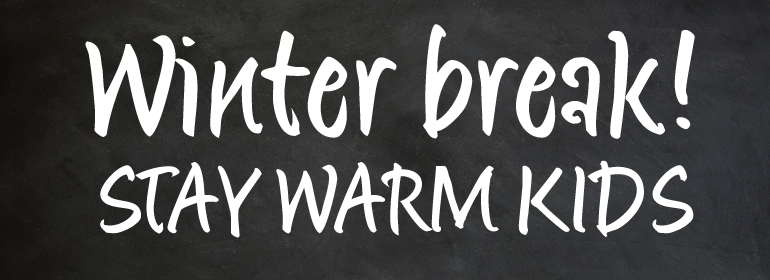
Matthia™
字体品牌: Linotype(Monotype) 设计师:Kurz,Dieter 字体分类: 字体属性:外文 字符集:Unicode 发布时间: 2018
1994年,Dieter Kurz在设计了Matthia。这是一种细长流畅的笔刷手写字体设计。Matthia的字符具有手写字体风格,但又几乎笔直,这使其既含蓄又生动,动静结合。该字体让人想起20世纪50年代流行的广告字体,用途极为广泛。Matthia适合于小尺寸的短文字或海报上的大标题。
Matthia是TakeType字体库的一部分,该字库包含了从1994年至1997年Linotype的International Digital Type Design Contest的获奖作品。
Dieter Kurz designed Matthia in 1994. It is a slender, flowing brush script design. Matthia's characters are in a handwritten style yet stand almost straight, making it a mixture of reserved and lively, of static, and dynamic. The font is reminiscent of advertisement typefaces popular in the 1950s, and is extremely versatile. Matthia is suitable for short texts in small point sizes, or large headlines on posters.
Matthia is part of the TakeType Library, which features the winners of Linotype's International Digital Type Design Contest from 1994 to 1997.